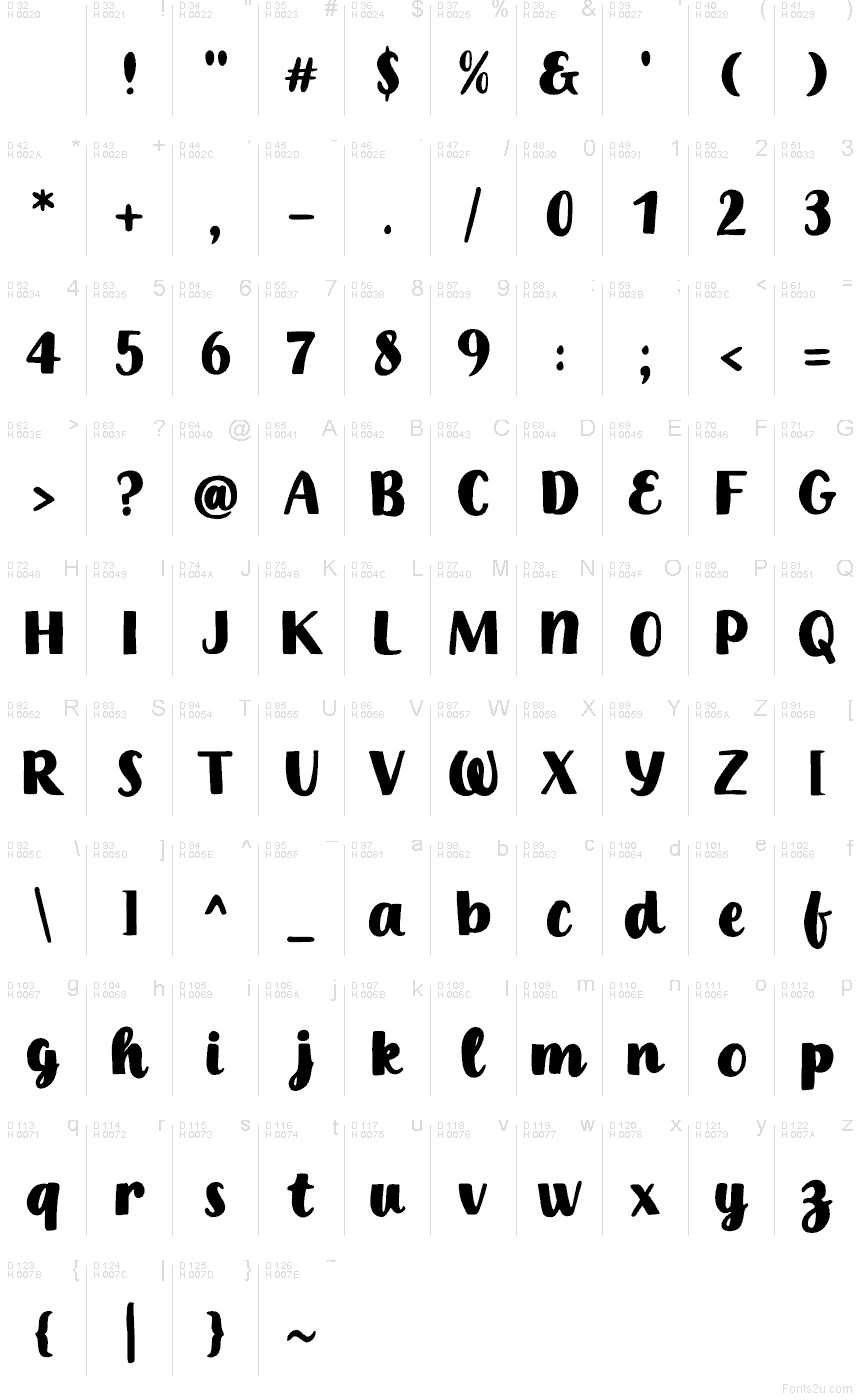
Lost Writting od Hello Good je bezplatné písmo s efektem štětce, které se vyznačuje hladkými, zaoblenými tahy a rukopisným rytmem, jenž působí spíše vyrovnaně než drsně. Písmena mají jemné křivky, kompaktní tvary a ležérní styl, který dodává designu autentický rukopisný dojem, aniž by působil nepřehledně.
Lost Writting skvěle funguje u logotypů, titulků na plakátech, obalů produktů, citátů v grafice nebo příspěvků na sociální sítě, kde je potřeba styl štětce, který působí osobně a bezprostředně. Toto bezplatné písmo se také hodí pro kavárenské menu, textilní štítky a krátké redakční doplňky, protože jeho rovnoměrná textura zachovává čitelnost a přitom stále nese jasný rukodělný charakter.